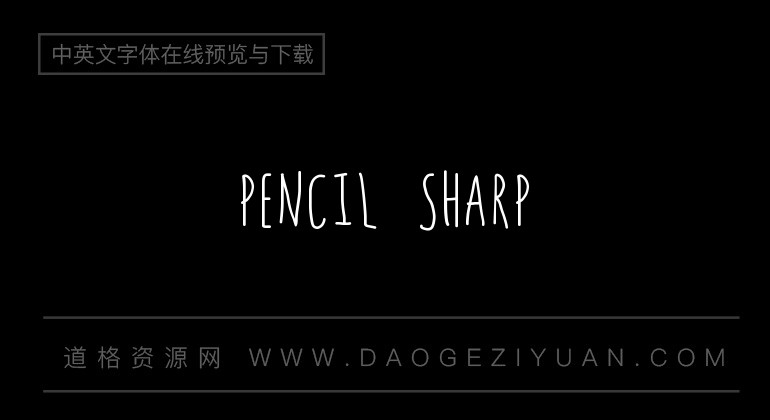
Pencil Sharp
Pencil Sharp 是一款字体,它是一款易读性较强的细节字体,有着清晰的细节和较大的字符间距。它可以用于标题和头部,也可以用于正文内容,适合用于报纸、杂志、网页等。它有着简洁的设计,可以让文字更加清晰易读,而且还有许多不同的字体可供选择,可以让你的文字更有特色。
Pencil Sharp是一款非常不错的手写艺术字体,具有很好的视觉感,适合于文化类的宣传设计、商业类品牌的广告和产品包装设计以及个性化文字排版等较多场景。